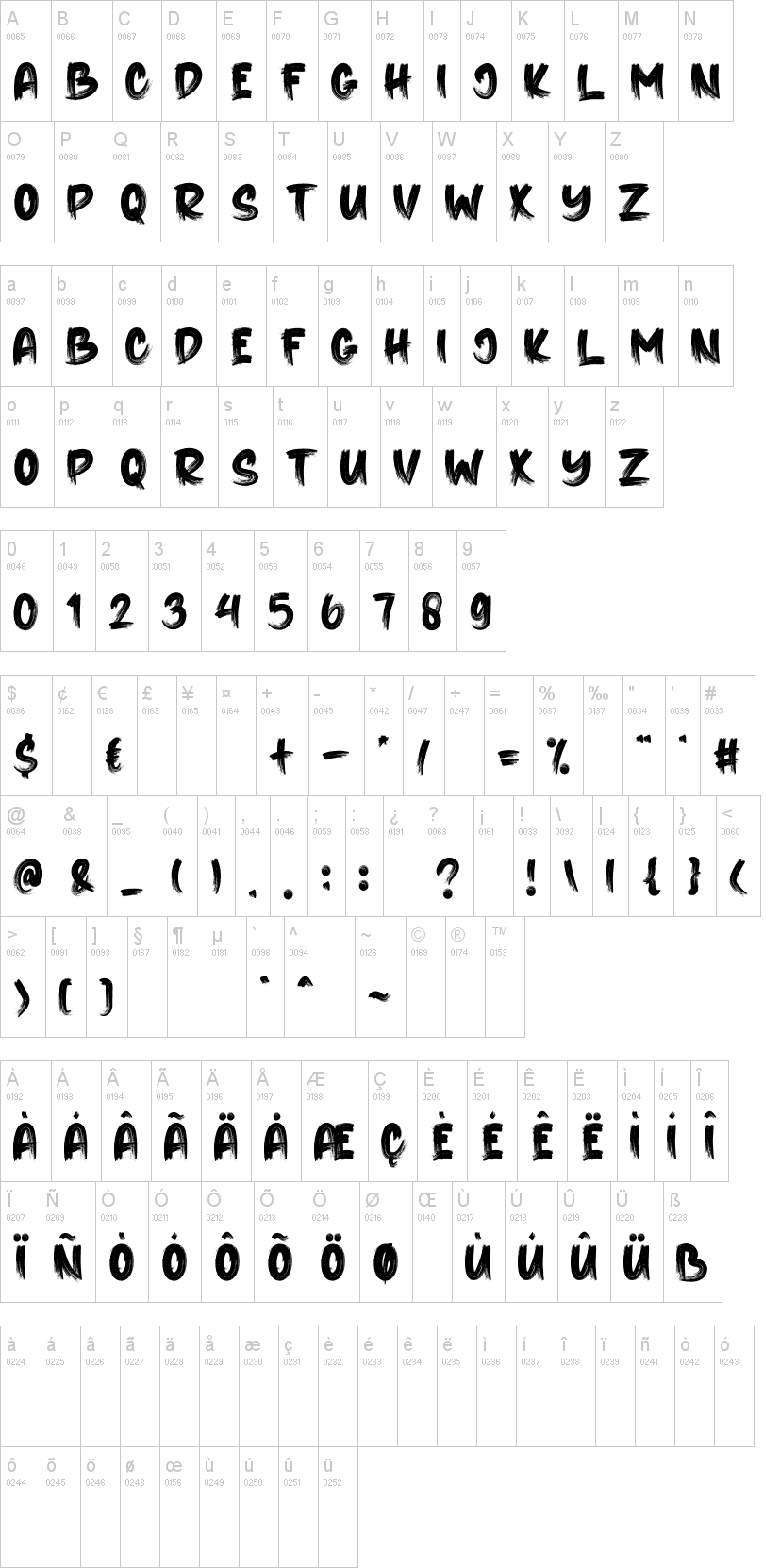
Thorn 字体是由英国设计师 Thomas Bewick 创造的一款英文字体,它具有独特的风格,具有粗犷、粗糙的线条,它的字形更加抽象,有着更加几何的结构,更加简洁、清新、大胆,更具有时尚感。Thorn 字体也是一款非常适合用于标志、海报和品牌设计的字体,它的简洁线条能够更好地表达设计者的创意,令设计更加出色。内容介绍
Thorn是一款非常不错的手写艺术字体,具有很好的视觉感,适合于文化类的宣传设计、商业类品牌的广告和产品包装设计以及个性化文字排版等较多场景。